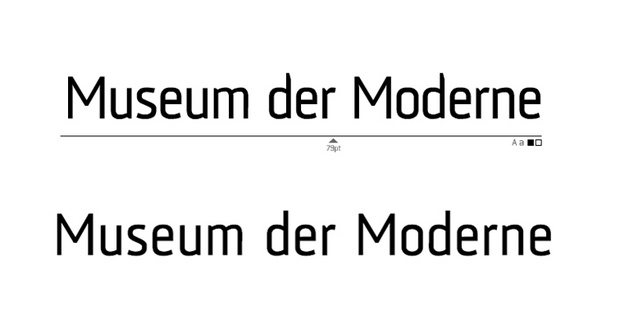
Leider nicht, aber ich meine, dass designkraft.at das gestaltet hat oder zumindest beteiligt war. Vielleicht hilft’s :-D
"What font is" hat sie mir ausgespuckt, ich wäre selbst auch nie draufgekommen, dass ein dänischer Designer für ein österreichisches Museum den Logofont liefert ;-)
Aber die Schrift ist doch nicht exklusiv für das Museum erstellt worden, oder? Ich kann mich nämlich daran erinnern, dass sie mir schon mal bei einem Verlag über den Weg gelaufen ist, für den ich gearbeitet habe. Die Klampenborg war dort eine der CD-Schriften einer Zeitschrift.
Nö, das ist sie nicht. Ich hätte als Museumskurator aber auf Europa gepfiffen und erst mal geschaut, ob das eigene Land nicht eine ebenso passende Schrift im Angebot hat. Das meinte ich mit "geliefert" :-) Schön und passend ist sie ja, die gute ;-)
Hab sie schon … AF Klampenborg Regular heißt sie.
Eingebettet wird sie aber als ToKlampenborg, hier aus der Schrift rausgekratzt:
©Henrik Kubel. Distributed by Acme Fonts, London.
Ist die kundenspezifisch modifiziert? Oder hat das To eine andere Bedeutung?
Ich denke dass die Schriftart Klampenborg heißt, wobei AF der Hinweis auf ACME Fonts ist, und die Schriftdatei ToKlampenborg (was auch immer To heißen soll). Analog verwendet Apple als Schriftart die Myriad, die einzelnen heißen dann MyriadApple-Text oder MyriadSet-Medium usw.
Soweit kein Widerspruch.
Genau da steckt aber u.U. eine Namenskonvention dahinter?
Das sind aber nicht immer die Standardversionen der Schrift? Teilweise werden die als OEM zugekauft und haben Anpassungen an das jeweilige System? Das wäre nett zu wissen. Manchmal hat man PDF mit eingebetten Schriften an denen man Änderungen vornehmen will. Und da kann da schon der Unterschied relevant sein, besonders wenn die Bearbeitungskette über verschiedene Plattformen gehen.
Ich denke, Uwe hat Recht, und das "To" bezieht sich auf die Modifizierung. Das würde dann auch den Unterschied im beigefügten Muster erklären (siehe "d").
Das fiel mir noch gar nicht auf, so genau hab ich wohl nicht hingeschaut. Die Modifizierung wird des Rätsels Lösung sein.